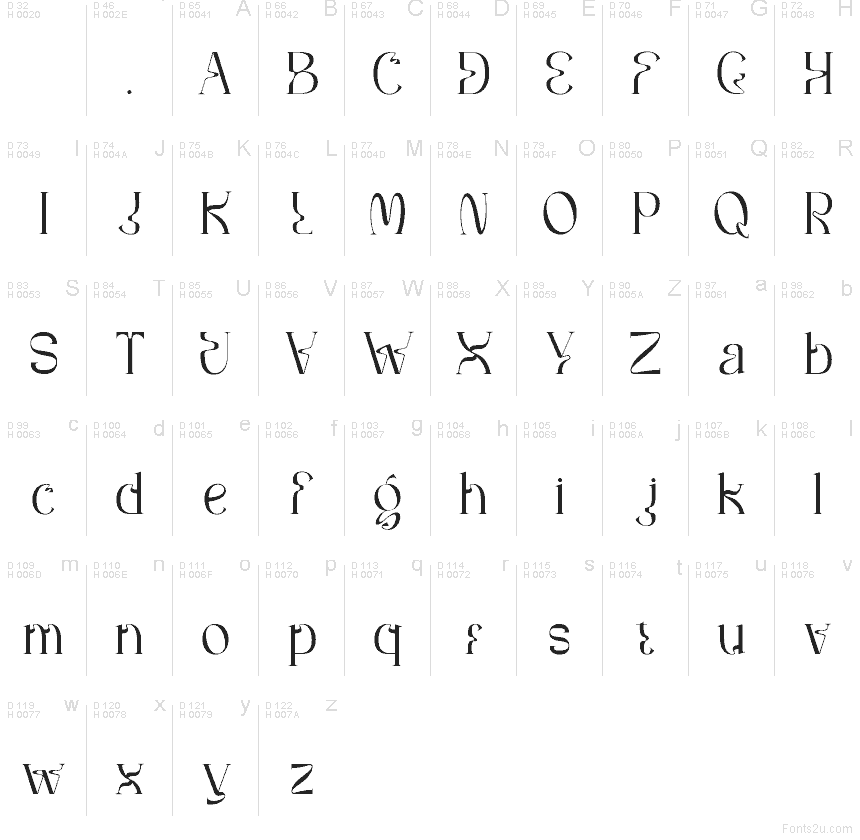
Gaykin od Cadence je bezplatné retro písmo typu display, které zaujme vysokými, úzkými siluetami a zakřivenými patkami, jež dávají písmenům až divadelní nádech. Rytmus písma je obzvláště výrazný tam, kde se hladké vertikální tahy setkávají s klesajícími ocásky a směrem ven směřujícími výkyvy, čímž vzniká vytříbená, mírně excentrická textura, která přesahuje rámec běžného retro stylu.
Tento charakter skvěle vynikne na obalech butikových produktů, v jídelních lístcích, na obalech alb, v módních redakčních materiálech nebo jako nadpis plakátu, kde písmo plní dekorativní roli. Jeho rozmáchlé křivky a ostré zakončení dodají krátkým textům, beauty etiketám i pozvánkám na akce historický nádech bez potřeby dalších ozdob.
Prezentace a vizuální ukázka písma Gaykin Regular
Mapa znaků písma Gaykin Regular
Mapa znaků písma Gaykin Regular: Základní latinka, strana 1
Glyfy písma Gaykin Regular — Základní latinka, strana 1